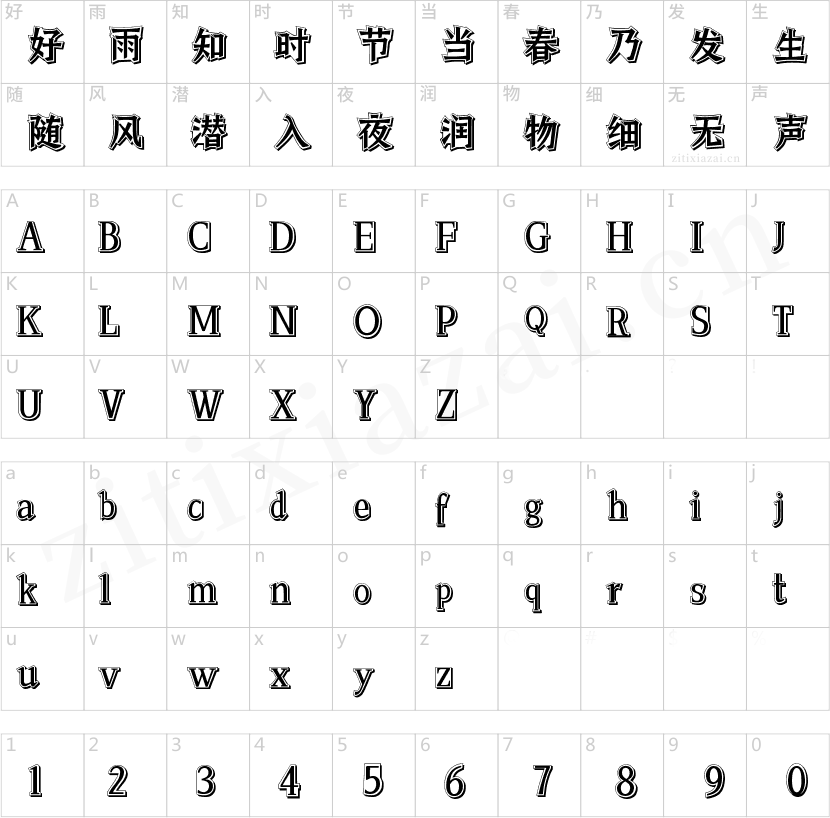
壹心风潮宋
壹心风潮宋,这款字体结构工整、笔画清晰,兼顾美观与易读性,适用于标题、正文、海报、包装、LOGO 等多种场景。字形优雅稳定,风格百搭耐看,适配日常排版与创意设计,让文字呈现更舒适、更具质感。壹心风潮宋一笔一画,皆是细节,以均衡的比例、流畅的线条打造舒适视觉体验,字形端正大气,风格简约现代。无论是商业设计、品牌宣传还是日常排版,都能轻松驾驭,让文字更有格调与力量。壹心风潮宋字体下载。